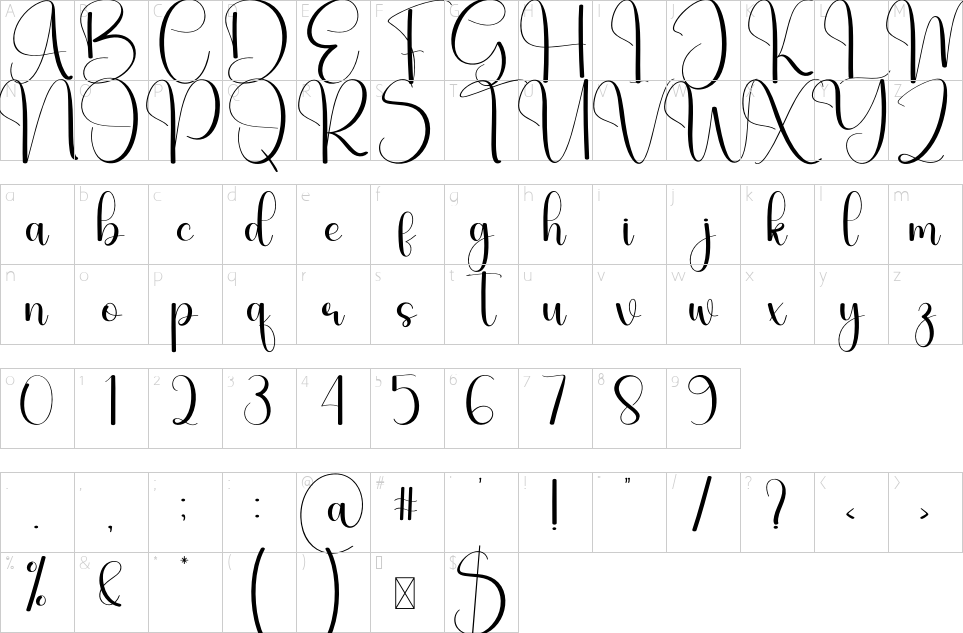
Esta fonte chamada Autumn foi criada por scratchones e está disponível para download tanto para Windows quanto para Mac. Ela carrega um ar descontraído e misterioso, como as folhas douradas das árvores no outono. Suas linhas fluidas e detalhes sutis criam um equilíbrio perfeito entre seriedade e sofisticação, tornando-a uma escolha excelente para designers que buscam um estilo elegante para suas criações digitais. Com seu design cuidadosamente projetado, a Autumn font é ideal para uso em nomes de negócios, design editorial e até mesmo para criar um toque especial em logotipos ou mensagens em redes sociais. Sua facilidade de uso e versatilidade a tornam um recurso indispensável para qualquer designer. Com uma incrível versão gratuita, você pode explorar a beleza deste design único e permitir que a Autumn font seja a a cara de suas próximas criações.